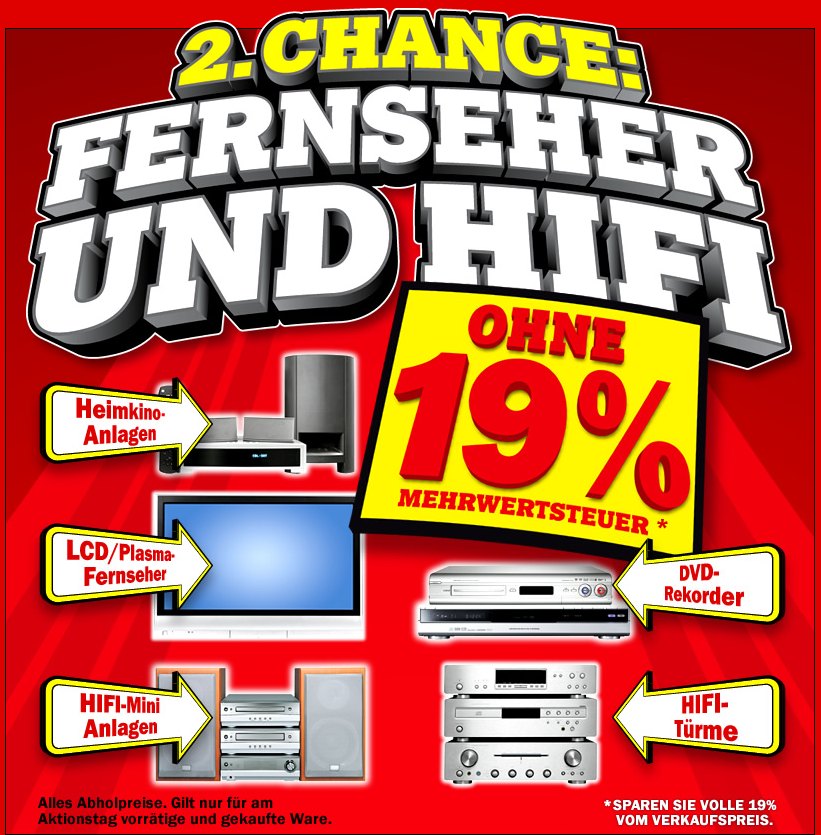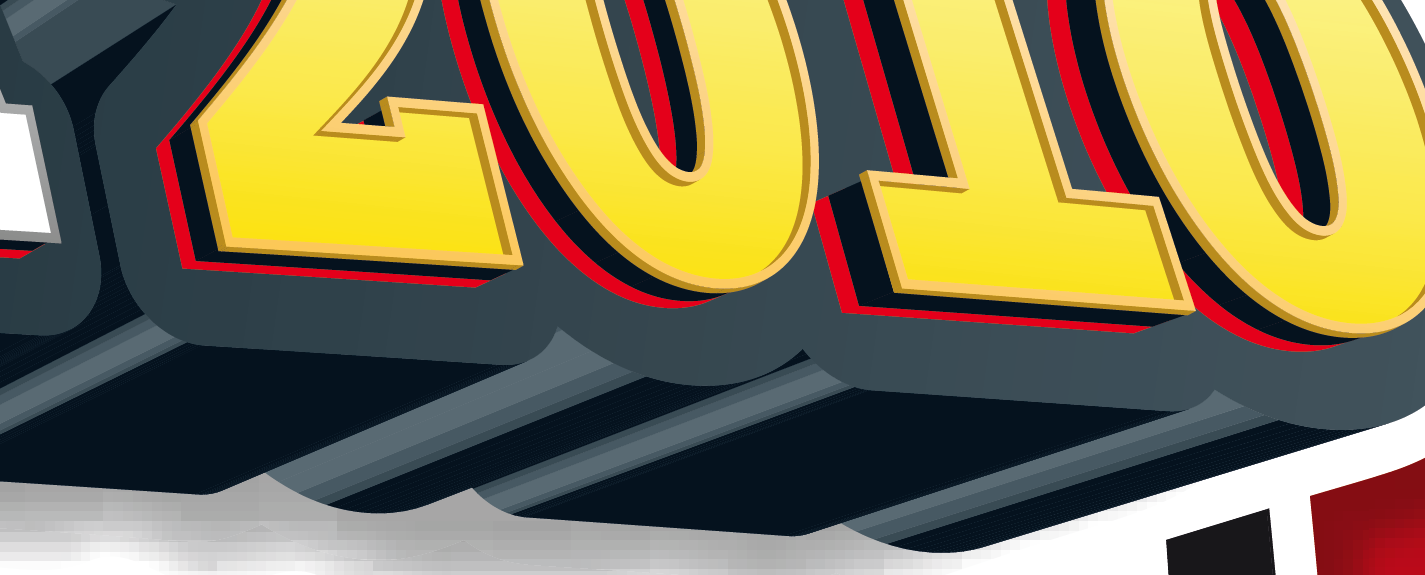
3d-texteffekte in illustrator
ich hab einen kunden her, der wünscht sich sein logo im mediamarkt-3d-style.
ähnlich wie hier:
über die 3d-funktion extrudieren erreiche ich zwar ähnliche ergebnisse, allerdings scheitere ich immer mit den farben und verläufen im detail. der ganz filter ist auch sehr buggy und rechenintensiv. ich dachte erst das die effekte vom mediamarkt-prospekt mit maya oder anderen rendering programmen erstellt wurden, dann habe ich mir mal eine pdf runtergeladen und gesehen das die effekte reine vektoren sind.
hat jemand eine ahnung wie man sowas erreicht? gibts dafür plugins?
vorallem die lichteffekte, bevel und rahmen innerhalb der schrift sind schwer aus dem plugin herauszukitzeln. man bekommt zwar einiges hin, wenn man verschiedene filter übereinander legt, aber ich bin mir sicher es gibt dafür auch eine einfachere lösung. beim MM sieht alles irgendwie komplexer aus, jedoch geordnet (wennich die pdf im illustrator öffne). irgendwie bekomme ich es nicht so hin. hat einer ’ne ahnung wie man diesen effekt erreichen kann?
hmm. schade ich habe keine rendering tools und auch so keine ahnung von den programmen.
kennt jemand paar nette plugins die sowas erledigen können? notfalls auch für photoshop.
ich hab jetzt einen ähnlichen effekt simuliert, mit 3d-extrudieren und diversen farbverläufen,
umrandungen und füllungen. so richtig zufrieden bin ich noch nicht – mal schaun was der
kunde meint.
jo. habs mit illus halbwegs hinbekommen, auch wenn die MM-schriftzüge mehr details haben.
wenn noch jemand 'ne gute lösung (tutorial, plugin, software) kennt – immer her damit.